Font balon adalah font dekoratif yang lucu, baik berupa bentuk balon maupun yang memiliki efek seperti balon.
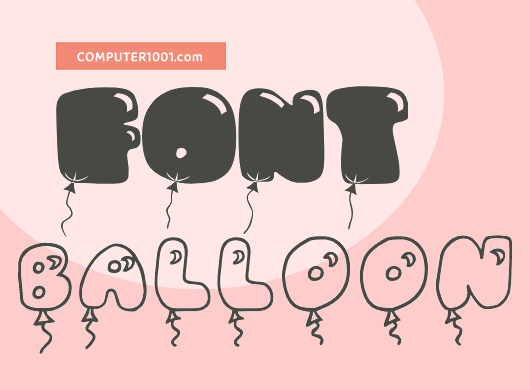
Font balon juga sering ditemukan pada gaya font gelembung (bubble font) dan font mengkilap (shiny font / glossy font).
Untuk itu, artikel ini menyajikan semua gaya font yang keren tersebut.
Download Font Dekorasi Balon
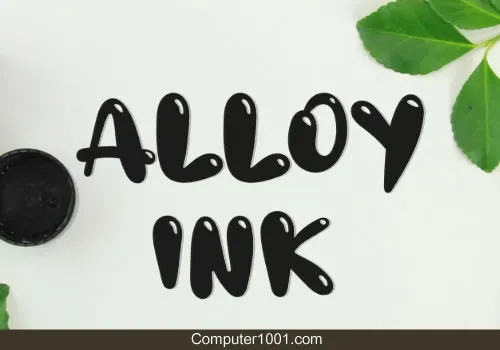
Font yang semuanya huruf besar dan memiliki angka 0 – 9, serta tanda baca, operator matematika, dan tanda kurung.
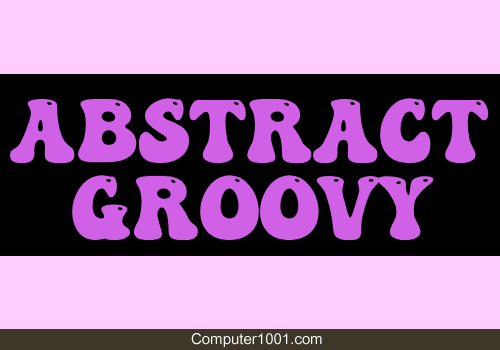
Abstract Groovy juga memiliki huruf besar semuanya.
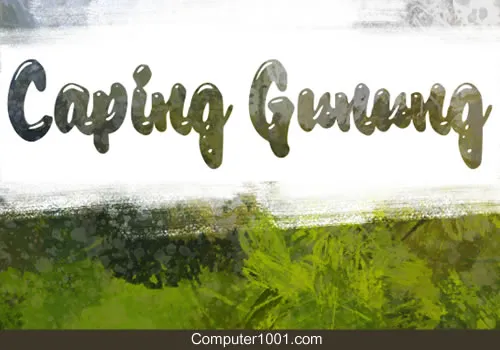
Caping Gunung memiliki huruf besar dan kecil, angka 0 – 9, serta simbol lainnya.
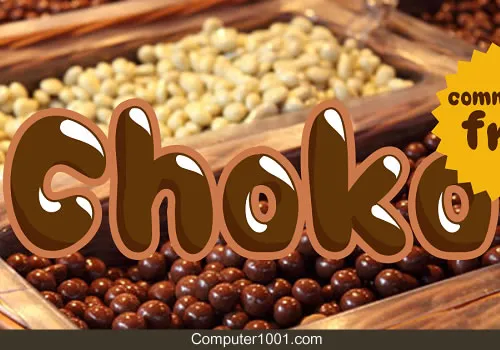
Memiliki 5 gaya berbeda, termasuk gaya shadow dan highlight, yang bisa ditumpuk di atas satu sama lain untuk membuat teks multi warna.
Font ini memiliki koleksi karakter yang lengkap, termasuk huruf tanda aksen.
Huruf besar font ini ada tali, seperti yang diikat pada balon.
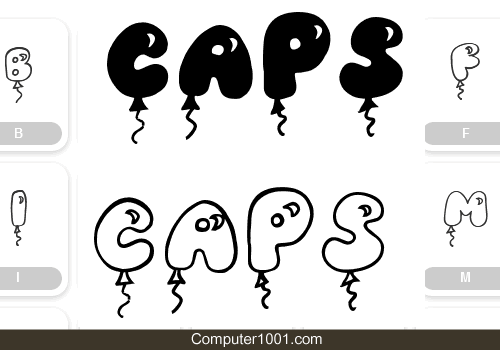
Font kartun yang lucu ini juga ada tali dan memiliki 2 variasi, yaitu solid dan outline.
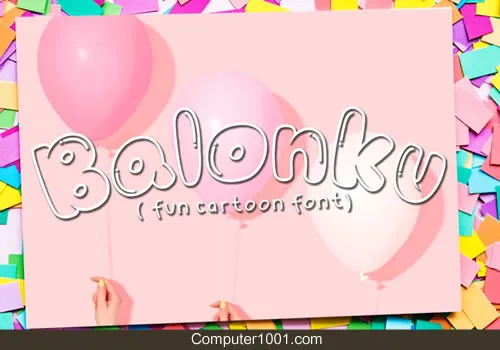
Balonku terinspirasi dari bentuk gelembung sabun atau balon; yang bernuansa kartun, lucu, dan kekanak-kanakan.
Font bergaya tulis tangan yang semuanya huruf kecil, dengan setiap karakter ditaruh dalam balon yang terikat tali.
Balloonish memiliki bentuk yang menggelembung dan tanda kurung kurawalnya {} berbentuk balon.
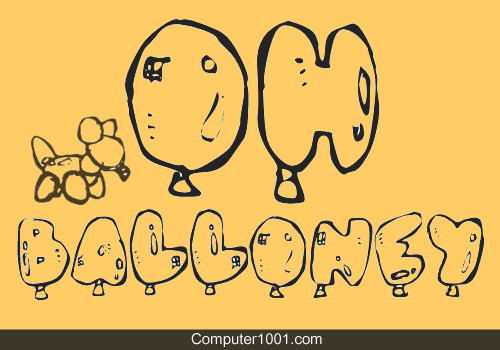
Font bergaya outline ini seperti goresan tangan yang agak berantakan dan compang-camping.
Semuanya huruf besar, dengan bonus ilustrasi boneka anjing yang lucu.
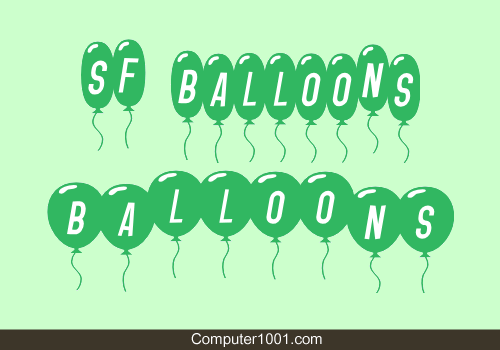
SF Balloons memiliki 4 variasi, yaitu bentuk ramping dan gembung (reguler dan italic).
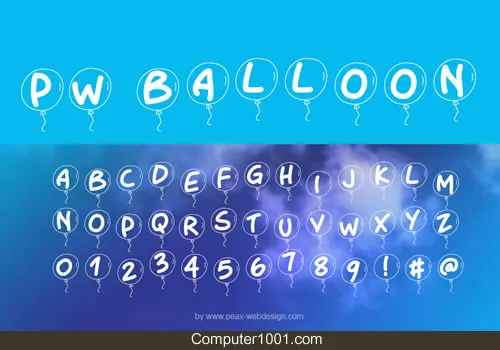
Font dengan karakter yang berada di dalam balon yang transparan.
Font balon bentuk hati yang cantik. Cocok untuk desain tema Valentine dan pernikahan.
Font dengan karakter hiasan balon bentuk hati.
Font balon dengan hiasan gambar awan dan burung camar.
Font kartun lucu dengan tanda silang.
Setiap karakter pada Tiger Balloon memiliki hiasan motif harimau.
Font balon dengan gambar muka kartun yang lucu.
Font ini memiliki efek kerut yang akan cantik sekali saat diberi efek teks.
Gas Huffer Phat juga kelihatan cantik bila diberi efek teks. Cara membuatnya akan dibahas pada tutorial yang lain.
Font kartun katak sedang memegang balon berisi huruf, angka, dan tanda baca.
Font gambar kelinci sedang memegang balon berisi karakter.
Cool Balloons memiliki huruf besar dan huruf kecil, serta tanda titik, koma, tanda seru, dan tanda tanya.
Font balon bentuk hati yang cantik.
Kumpulan font balon yang lucu dan keren ini cocok untuk desain grafis tema anak-anak, pesta ulang tahun, rekreasi, acara lomba, atau desain lain yang memberi kesan riang gembira dan playfull.
Contoh: desain banner, brosur, selebaran, poster, dekorasi pesta, kartu undangan, kartu ucapan, dan slide presentasi.
Keindahan font akan makin terlihat bila diberi efek teks 3D dan gradasi warna, yang bisa kita buat di Word, PowerPoint, atau aplikasi gambar lainnya.
Selain itu, kita juga bisa mengkombinasikan 2 gaya font (solid dan outline) dalam sebuah desain, agar tampilannya makin menonjol dan menarik.